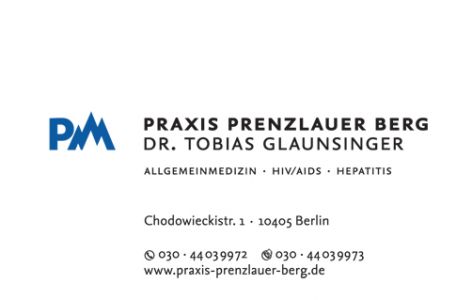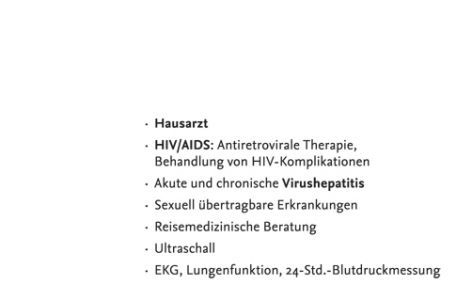
ich bin auf der Suche nach Beipielen für typographisch ansprechende Visitankarten. Im Netz gibt es zwar viele Beispiele, nur mit dem "typographisch ansprechend" ist es eben nicht soweit her. Hat jemand von Euch etwas zu zeigen?
Überhaupt, wie seht Ihr das mit der Gestaltung von Visitenkarten? Sagen wir für einen Autor, Setzer oder eben Typographen: wie sollte eine solche Karte gestaltet sein? Ja, wie gestaltet Ihr Eure Karten? Hat jemand den Mut seine Karte hier zur kritischen Beurteilung zu posten? Dann kommen doch bestimmt mögliche Hinweise?!
Ich besitze keine Visitenkarten, aber meine wären am besten minimalistisch, typolastig und haptisch (Stanzung oder Prägung).
Die Seiten von Martin Z. Schröders »Druckerey« sind auf jeden Fall einen Klick (und mehr) wert. Martin war hier früher öfter mal zu lesen, ist aber wohl im selbstgewählten Funkloch verschwunden – oder taucht nach dieser Steilvorlage mal wieder auf.
Das ist doch ein weites Thema.
Meines Erchtens werden Visitenkarten in der Regel überschätzt. Eine Visitenkarte ist kein Werbemedium, sondern soll lediglich Zettel und Stift zum Aufschreiben eines Kontaktes ersetzen. Mehr nicht.
Ich selber habe mein Foto auf meiner Visitenkarte (diesen Trick habe ich von einem Immobilienhai gelernt). Warum? Wenn man sich auf einer Messe trifft oder ein potentieller Kunde Interesse an Leistungen hat, spricht er in der Regel mit mehreren Dienstleistern, hat anschließnd einen Haufen Unterlagen und Visitenkarten und weiß nicht mehr so recht, wer wer war. Aber gerade bei uns ist die persönliche Komponente nicht zu unterschätzen. Man muß sich ja auch verstehen. Und bei meiner Visitenkarten werden sie immer wissen, von wem sie kam - im Positiven wie im Negativen. So kam es z.B. vor, daß ein Reiseveranstalter meine Vistenkarte suchte, weil er sich an ein Treffen von vor zwei Jahren erinnern konnte.
Puren Pragmatismus folgend mag das alles richtig sein. Gleichwohl, es geht natürlich auch anders: Sofern ich einen Gestaltungsauftrag zu vergeben habe, wird sicherlich derjenige Graphiker, Typograph, Designer schlechte Karten haben, der mir eine Karte mit Passbild überreicht, auf dieser mich seine Daten in einer Arial/Times/Word-Vorlagen-Mischung ärgern -- und selbst ich als Laie bereits hier sein gestalterisches Talent in Zweifel ziehen muss (selbst wenn es sich um ein Genie handeln solte).
Sofern ich einen Gestaltungsauftrag zu vergeben habe, wird sicherlich derjenige Graphiker, Typograph, Designer schlechte Karten haben, der mir eine Karte mit Passbild überreicht, auf dieser mich seine Daten in einer Arial/Times/Word-Vorlagen-Mischung ärgern
Ich habe mich – glaube ich – wohl nicht richtig ausgedrückt.
Die Visitenkarte mit dem Foto funktioniert natürlich nur, wenn der potentielle Kunde sie in der Hand hält, NACHDEM er mich kennengelernt hat. Dann habe ich nämlich schon einen Eindruck hinterlassen und die Visitenkarte dient nur noch der Kontaktaufnahme. BEVOR er mich kennengelernt hat, wirkt eine Visitenkarte mit Foto natürlich affig. Aber das nehme ich gern in Kauf. Anonyme potentielle Kunden interessieren mich nicht so sehr. Lieber solche, mit denen man redet, die man aber nicht aktiv aquiriert. Und wenn sie dann was brauchen, werden sie sich melden. Das ist nicht der schnelle Weg, Millionär zu werden. Dafür aber ein sehr nachhaltiger.
PS.: Was ich noch anmerken muß: meine Kunden kommen hauptsächlich aus dem touristischen Markt. Dort spielt Persönlichkeit eine sehr große Rolle bei der Wahl der Dienstleister und Partner. In anderen Branchen sieht das natürlich anders aus. Es gibt auch Branchen, da ist der Schein wichtiger als das Sein.
Das ist doch gerade die Gestaltungsherausforderung: Eine Karte mit Bild, aber nicht mit diesem schrägen Versicherungsvertreter-Look ...
zu dem PDF von Alfons habe ich eine Frage:
Im Text steht zu Wie Nummern machen?:
Eine andere Variante:
Phone ++41 (0)1 712 60 90
Ist das richtig? Das Plus erstetzt doch die Auslandskennziffer (also in Deutschland 00) – das Beispiel würde doch heissen: 0000. Ausserdem wird die Vorwahl-Null bei Angabe der Landeskennziffer nicht mit angegeben (soweit ich weiß). Kann das jemand bestätigen? Ansonsten fand ich die Gestaltungshinweise ganz gut.
Phone ++41 (0)1 712 60 90
Ist das richtig? Das Plus erstetzt doch die Auslandskennziffer (also in Deutschland 00) – das Beispiel würde doch heissen: 0000. Ausserdem wird die Vorwahl-Null bei Angabe der Landeskennziffer nicht mit angegeben (soweit ich weiß). Kann das jemand bestätigen?
Also ich hab mal bei Forssman/de Jong nachgeschaut:
Ein doppeltes Plus-Zeichen gibts da nicht (aus dem von dir schon genannten Grund ...); "+49" ist besser als "0049", weil das in manchen Ländern sonst zu Verwirrungen führt ... [im Übrigen ist die Angabe einer internationalen Vorwahl bitte auch nur bei einem international agierendem Unternehmer sinnvoll! Jemand, der Visitenkarten eh nur seinen Freunden im gleichen Land gibt, kann sich das sparen, das wirkt sonst lächerlich!]
Auch Forssman/de Jong sagen: "Die '0' vor der nationalen Vorwahl lässt man weg, wenn man die internationale Vorwahl davorsetzt." (S. 197)
PS: Die einzige runde Vk habe ich bisher von einer Firma bekommen, die - nachdem ich brav geliefert hatte - die "Hand gehoben" hat. Originalität tut's also auch nicht immer ... du wärest also quasi vorbelastet, ohne was dafür zu können. Mainstream muss nicht immer schlecht sein.